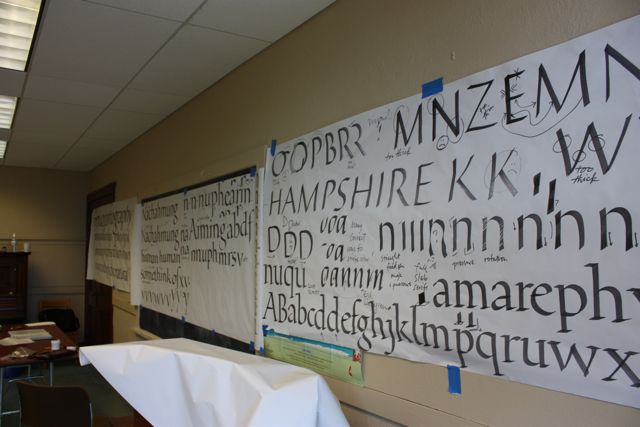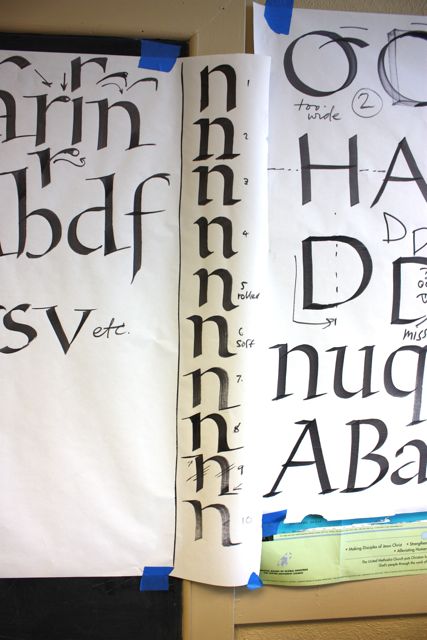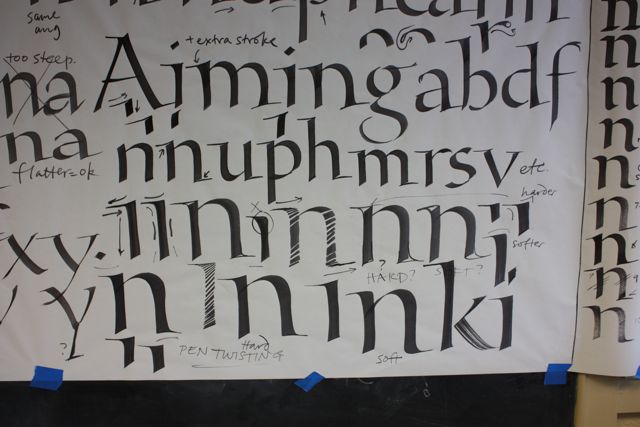
シカゴから2
今回シカゴではJulian WatersのRoman Minusculeを取りました。5日間のクラスです。
たまにはずーっと書き続けるのもよいかな、と思って取りましたが、本当に5日間朝8時半から夕方5時まで書き続けた1週間でした。幸せだ〜!
毎日卓球のユニフォームで登場のジュリアンでした。模造紙にどんどんデモンストレーションで書いてくれるので、とてもわかりやすく、自分のペースで書きながら見る事ができ、フラストレーションがたまらず、とてもよいクラスでした。
少し書いては前に集まってデモンストレーションを見るという形だと、早く書きたい!もっと書きたい!という気持ちで疲れますが、今回は、ヘルプが必要な時は手をあげてジュリアンを呼んで書いてもらったり質問したりできたので、これもとってもcomfortable!
クラスでは、foundational体の復習を含めて、写本や活字のトレースや模写から形を確認したり、いろいろなセリフを段階的に学んだりと、一歩一歩進みました。いろいろなペンの動かし方も確認できました。
確認は出来たけど、じゃあ書けるかというと難しい・・・。全然スムーズにはいきません。ペンを操作するのは、本当に練習するしかないんだな、きっと・・・。
簡単そうに書く様に見えるけど、難しいところに奥深さがあるのですね。
文字の本来備わっている美しさを判断、確認してそれを身につける。その基礎があってこそ、美しい線、美しい文字美しい空間を自分のものに出来るのです。
そのことが確認出来ただけでも、行った甲斐がありました。
やっぱり基本が大事。美しく文字を書くことが、すべてにつながり、その基礎を持たない限り、ある一定以上には進めないということです。ごまかしはきかなくなるということですね。それって見る人が見たらすぐわかることですよね。
地道に進むのが好きだから、いくらでもゆっくりと確認しながら行く事は苦ではありません。
がんばろうっと!
うわぁすごいですねー。でも一週間じっくり、見たり聞いたりしながら書くのは楽しそう♪ それにしても・・ いつもペンを握っていそうなmojitor-sさんですら、スムーズにいかないって感じるなんて・・・ 参りました!
じっくり書くことはなかなか出来ないので、こういう時間は本当に貴重で楽しかったです。
いえいえ、本当にスムーズになんて全然行きません・・・。やればやる程自分が出来ないってことがわかってきます。本当に奥深いものだからなんですねー。
きっと一生そう思っていくのでしょうね。
そういうものなのですねー、やっぱり。。。 出来ないって思うからもっとやりたいと思うし、進むことができる。。 ちょっとMぽい?(笑
読んでいてふと気が付いたのですが、確認しながらゆっくり進む、って一番苦手かもしれないです。がーん。全ての原因ここにあり。かも...